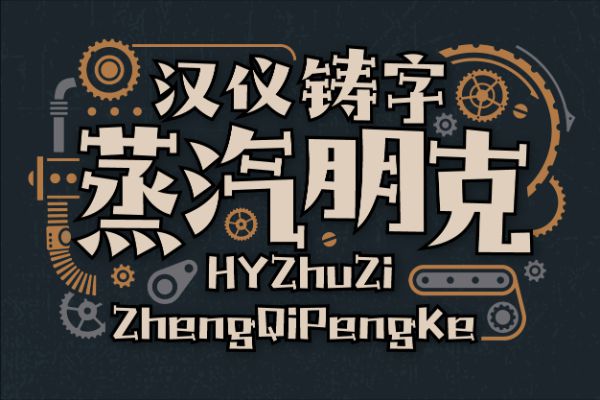
汉仪铸字蒸汽朋克 W
汉仪铸字蒸汽朋克是一款兼具朋克文化的叛逆气息与工业革命的科技浪漫的创意设计字体。这款字横细竖粗,横画两端有着螺丝帽一样的装饰衬线,增添机械装置的印象。字形转角干脆利落,撇、捺、点端点锐利,增添一丝童言无忌的叛逆感。每个笔画都成一定角度倾斜,字面也随着字形结构的变化而有轻微的宽窄高低的波动,带来蒸汽科技的动力感,和爵士乐一样的怀旧韵律感。整体风格乐观,叛逆、怀旧、可爱,适合作为标题字,用在绘本玩具、文创周边、综艺影视等场合。